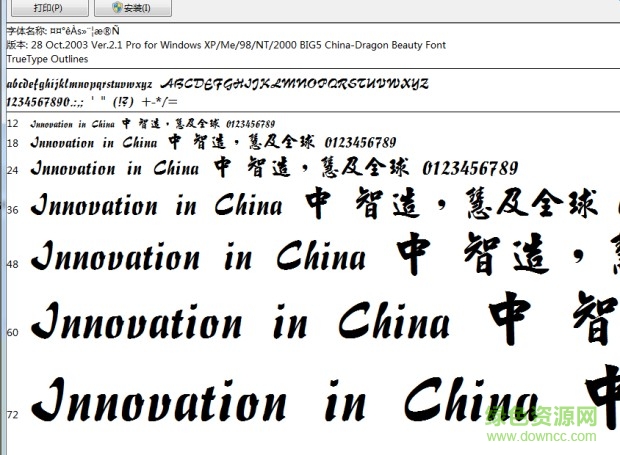
idhaoxing是什么字體?idhaoxing字體又叫中國(guó)龍豪行書,該字體筆力遒勁,點(diǎn)畫呼應(yīng),表現(xiàn)力非常出色,綠色資源網(wǎng)還有更多優(yōu)質(zhì)行書字體免費(fèi)提供,歡迎到綠色資源網(wǎng)下載!
1.行書是介于楷、草間的一種書體,寫得比較放縱流動(dòng),近于草書的稱行草;寫得比較端正平穩(wěn),近于楷書的稱行楷。
2.楷書與行書書寫時(shí),點(diǎn)畫的寫法,用筆需遵循的準(zhǔn)則,如中鋒,鋪毫,逆入平出,提按起主,藏鋒等都是一致的,只是行書書寫時(shí)比較舒展,流動(dòng)。